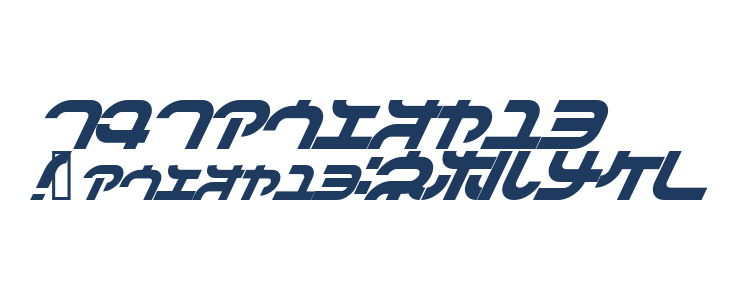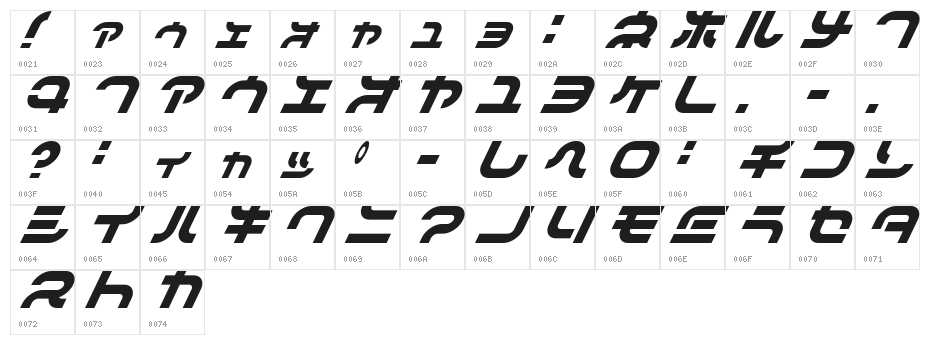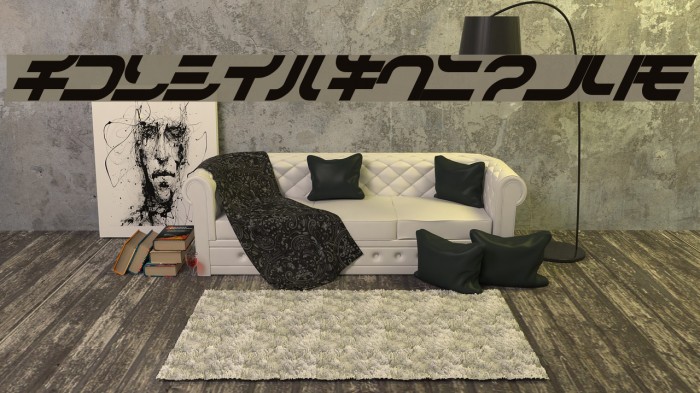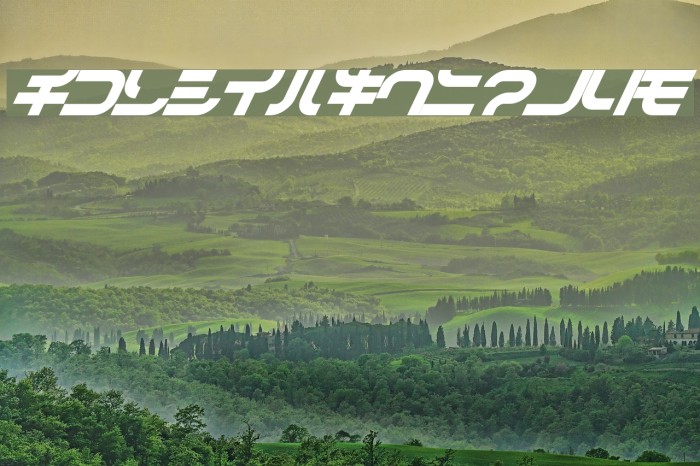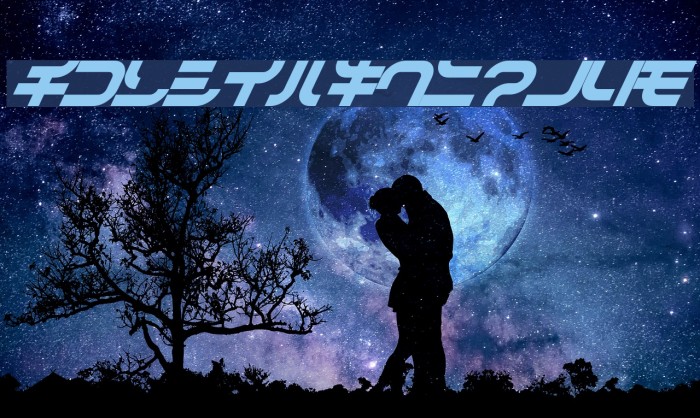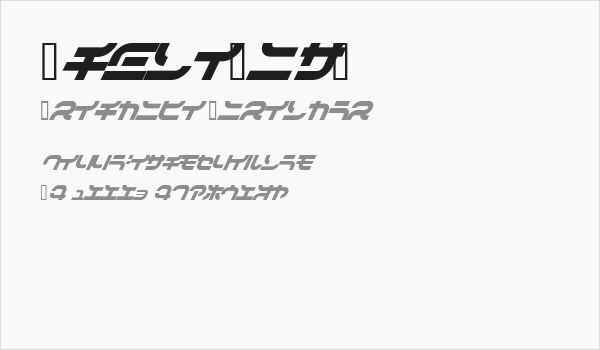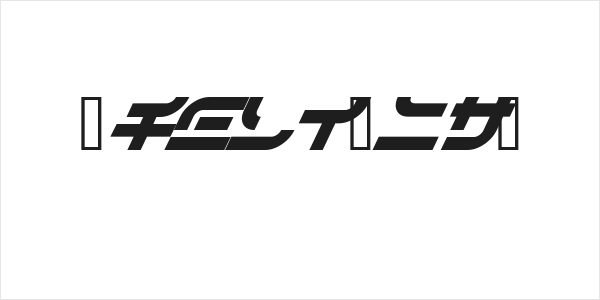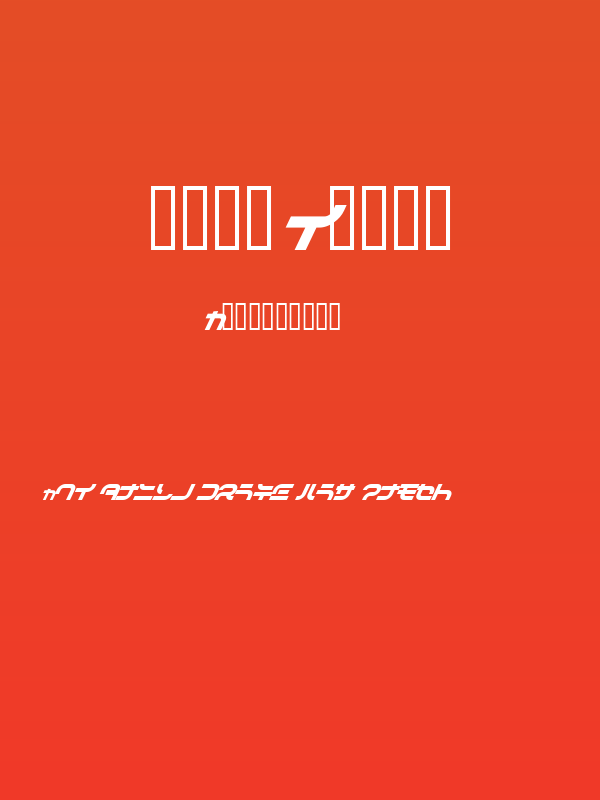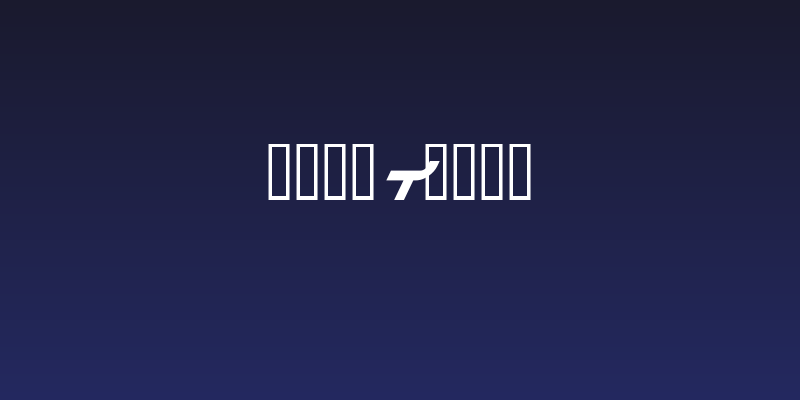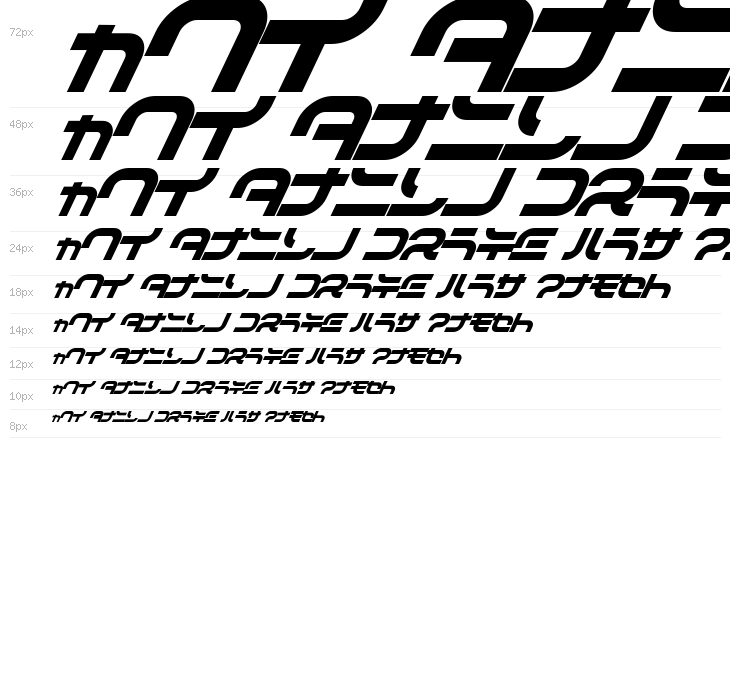
DanceMixR Font
| Progetti proposti | Ideal for projects that require a modern and dynamic look, such as sports branding, music album covers, or tech-related advertisements. |